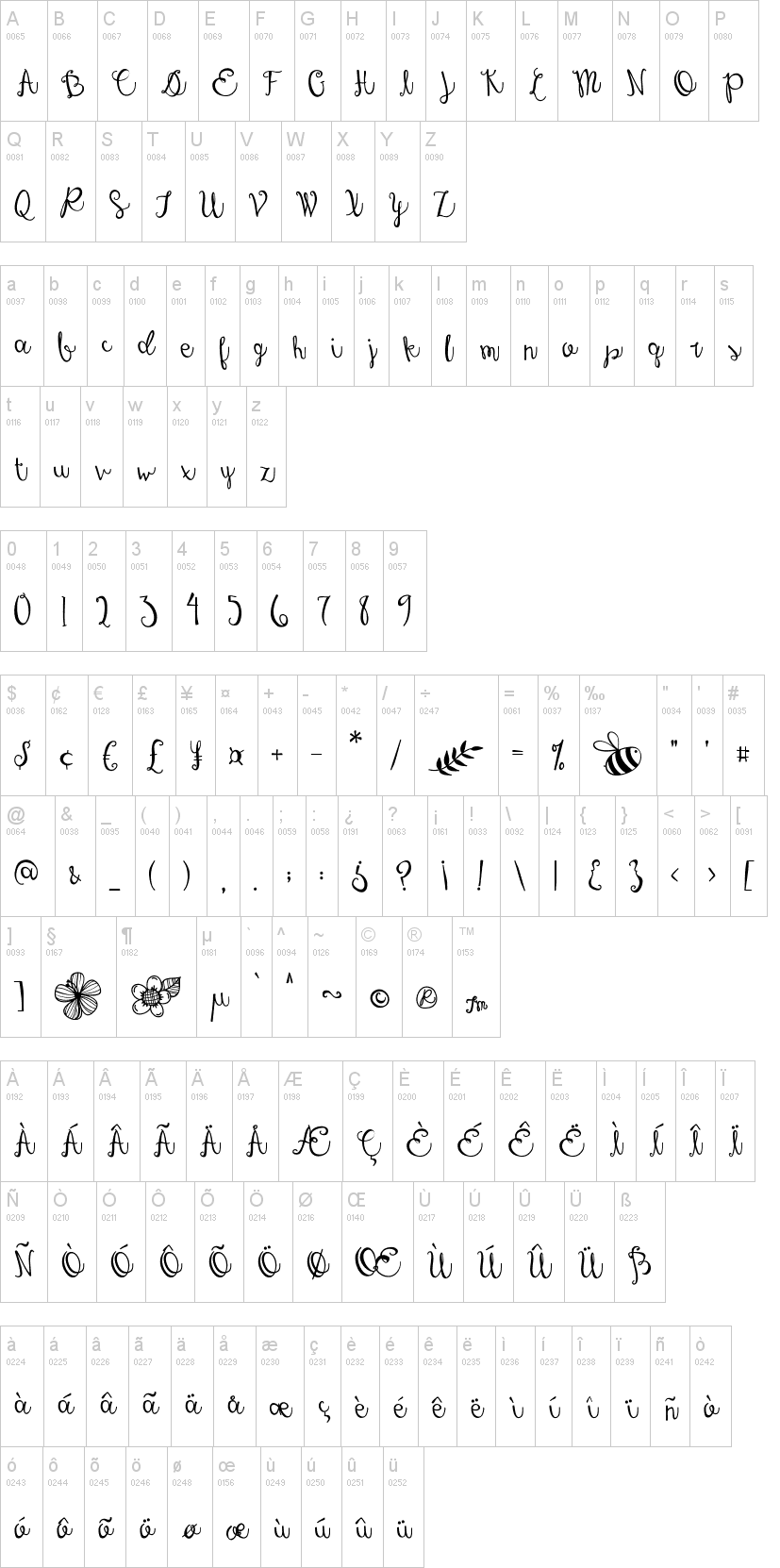
Austie Bost Dreamboat
Austie Bost Dreamboat 是一种手写风格的字体,它的创作灵感源自于美国西部的田园风情和旧时的手写信件。该字体的风格具有浪漫和优雅的特点,适合用于各种印刷品、宣传资料和个人设计项目中。Austie Bost Dreamboat 字体包含了大写字母、小写字母、数字、标点符号以及特殊字符,支持多国语言。如果你正在寻找一种优雅、浪漫的手写风格字体,那么 Austie Bost Dreamboat 可能会是一个不错的选择。
Austie Bost Dreamboat是一款非常不错的手写艺术字体,具有很好的视觉感,适合于文化类的宣传设计、商业类品牌的广告和产品包装设计以及个性化文字排版等较多场景。